Presentando Santatipo (Feria del Libro Viejo)
Los pasados días 10 y 17 de agosto, se presentó Santatipo dentro de la Feria del Libro Viejo de Santander. Este año la temática de la misma era la «Gráfica Comercial». Para ello se diseño un gran programa que incluía unos interesante paseos por la ciudad para conocer como ha cambiado el panorama comercial. Además hubo una serie de charlas enfocadas al tema gráfico y entre ellas se habló de Santatipo como un proyecto que preserva ese material.
Ha sido una gran experiencia y sobre todo una agradable sorpresa ver el interés que hay por conocer y sobre todo conservar esa parte de la memoria de la ciudad a través delo Rótulos como elementos gráficos que trascienden a la calle y su identidad. De ahí que haya un incesante interés en protegerlos como Patrimonio Gráfico.
Las charlas sirvieron también para presentar lo que empieza a ser una colección de rescate, donación y recreación de rótulos de la ciudad. Para el proyecto esto ha sido un punto social importante, porque así se consigue llegar a la gente y hacerles partícipes del proyecto.
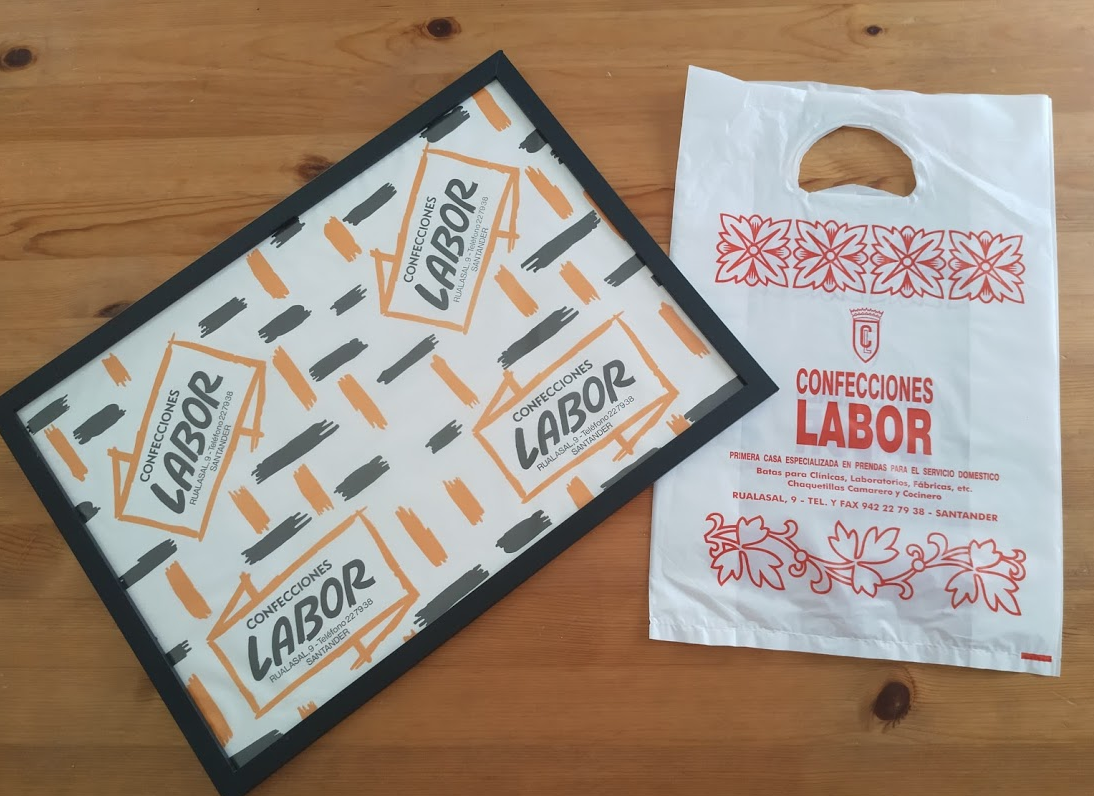
Material dado por Confecciones Labor que se expuso en la segunda jornada. Foto: Santatipo
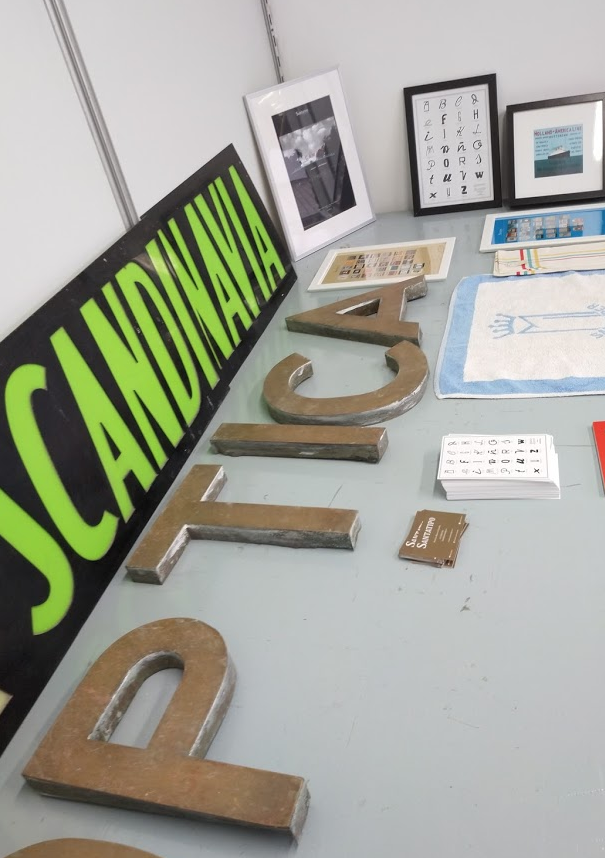
Materiales expuestos. Foto: Santatipo